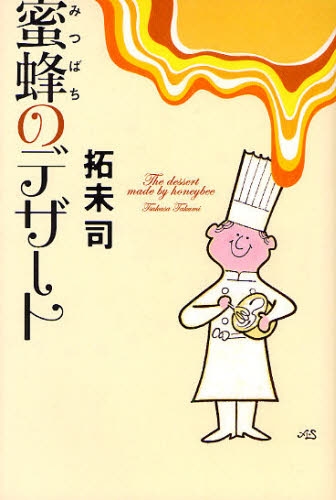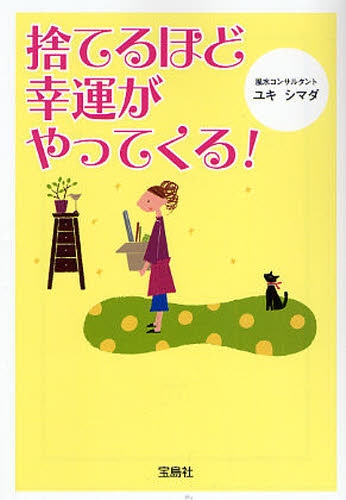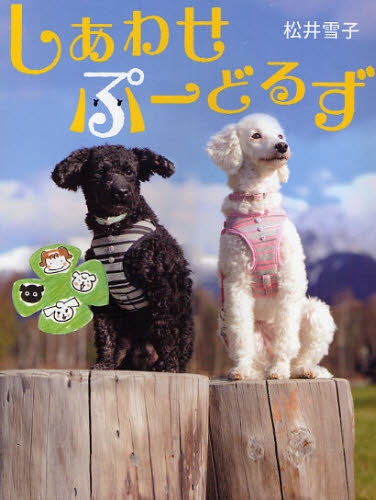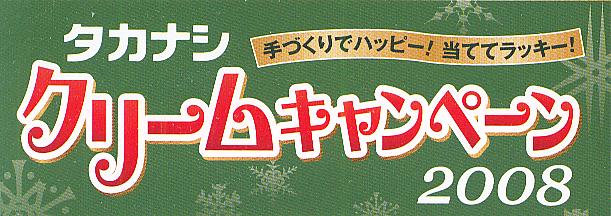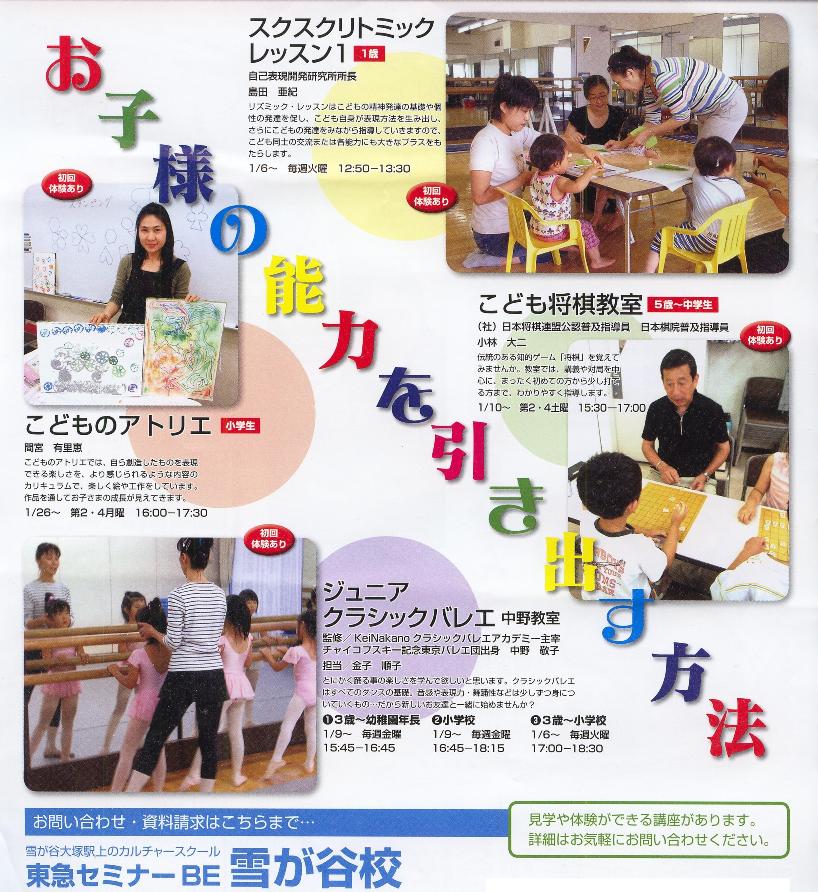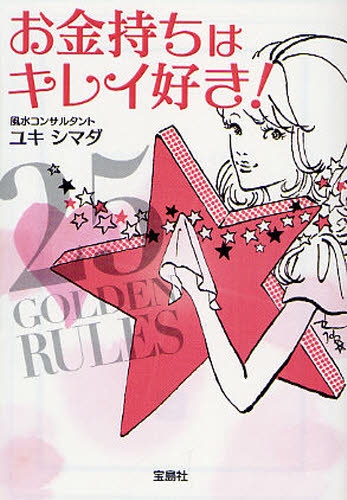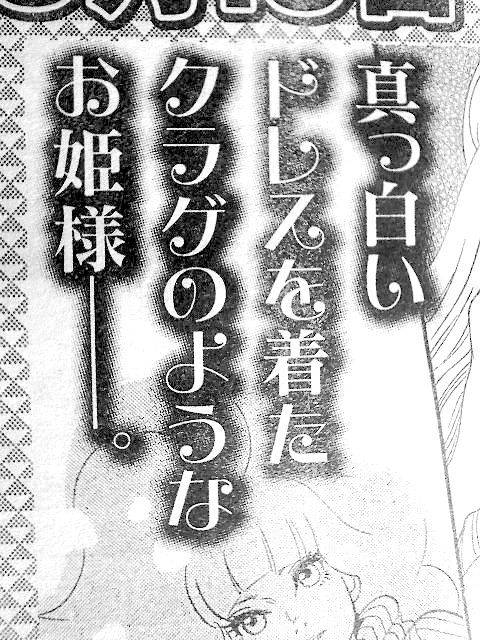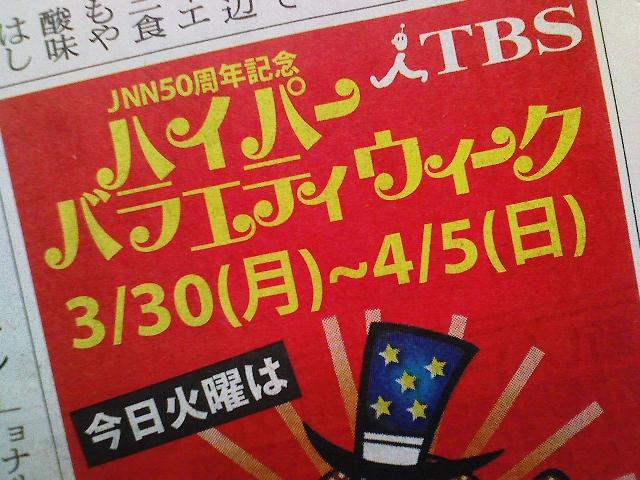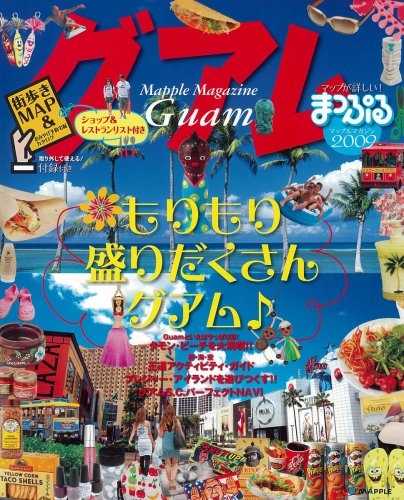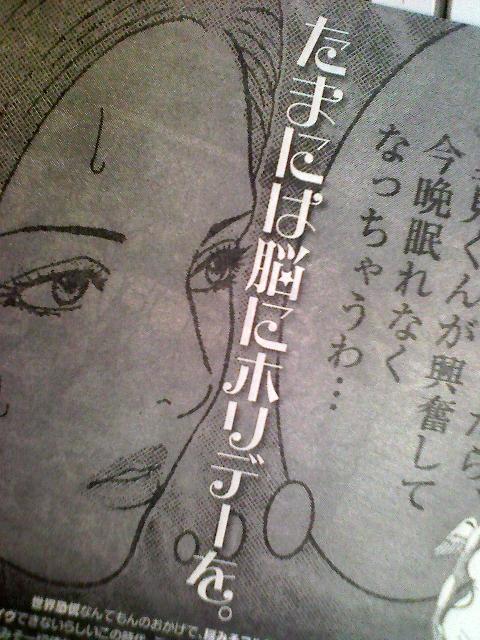
女性向け漫画雑誌、読者プレゼントページのタイトル。
えれがんと書体、使用例の投稿です。
ポプラ社『ライブオン CARDLIVER 翔』
まんが:あいやーぼーる
ストーリー:吉川兆二
「あ」に付いている濁点が浮いて見えるのでかなり気になります;
いかにも“なかったのであとから付けましたー”って感じで…
(>_<)
どうせなら、えれがんと書体の濁点「゛」を付けてくれたら良かったのにねぇ…と思いました。
そういう時のために「゛」を用意してあるのに…。
最近の雑誌には、本の内容とあまり関係ない、こういう付録がついている…。
これは、Myojoという老舗芸能雑誌6月号に付いていたトートバッグの外装。
太田垣康男という人の連載漫画の扉ページです。
書名:きせかえシールあそび
著者:講談社
発行:講談社
タレントのイメージとマッチして
スッキリと感じます。
えれがんと書体とスザンヌが、いい感じでフィットしてますね。
あ、あられ書体もたくさん使われている〜〜。
いつも読んでいるMacの月刊雑誌です。
小さなサイズの記事をiPhoneで撮影したので、
ちょっと歪んでいますが…。
あんぱんで有名なお店らしいです。
木に彫られた「えれがんと」は珍しいかも。
とてもキュートなフォントなので購入しました。
楽しい画像が作れそうです!